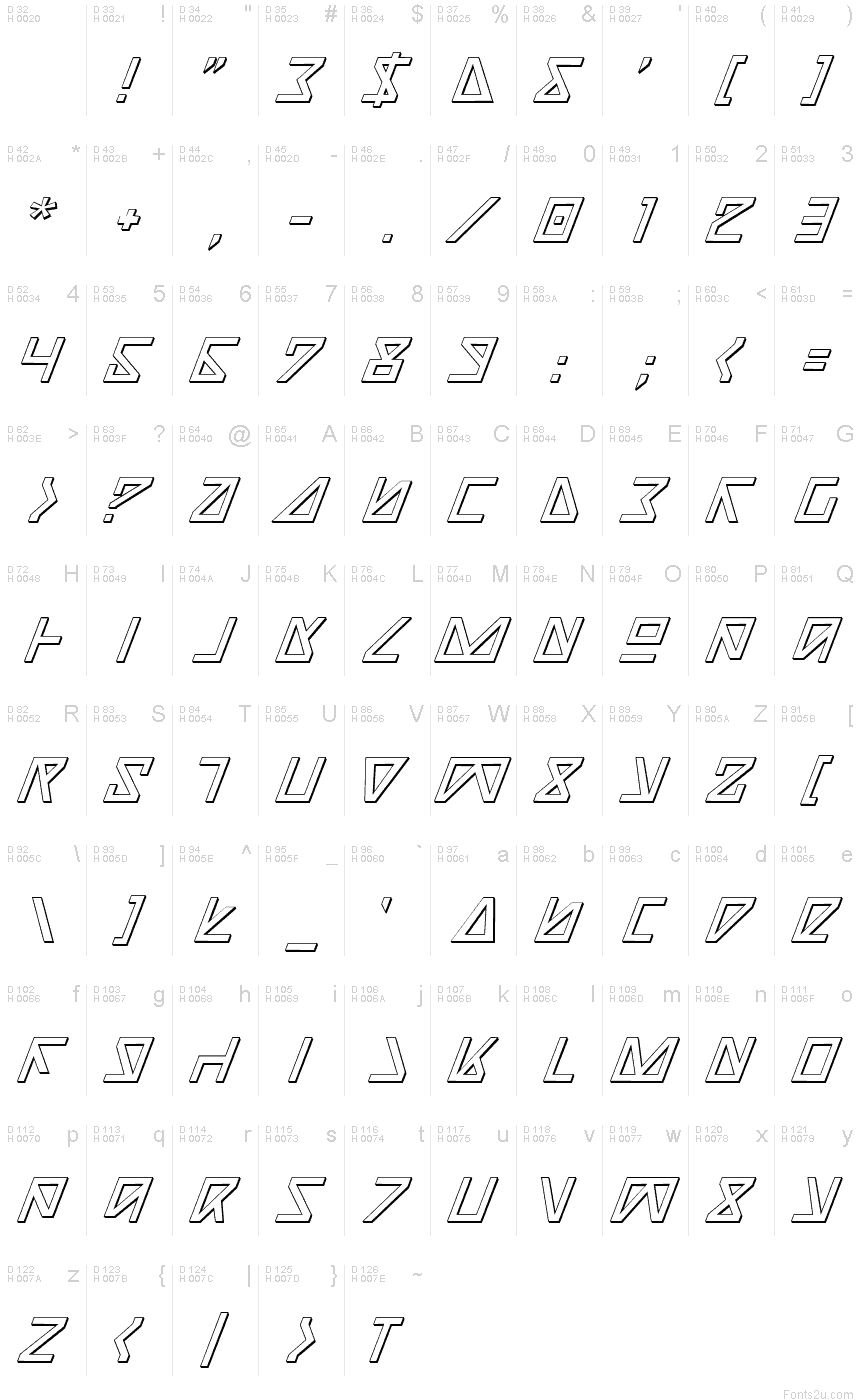
Nick Turbo Italic 3D to darmowy techniczny krój pisma typu display od Iconian Fonts. Wyróżnia się skośnymi, geometrycznymi konturami, ostrymi wcięciami i warstwowym efektem 3D, który nadaje każdemu znakowi wyścigowy, pochylony rytm. Kanciaste formy sprawiają, że projekt jest zwarty i mechaniczny, a otwarte wnętrza liter zapewniają czytelność nawet przy szybkim spojrzeniu.
Nick Turbo Italic 3D świetnie sprawdzi się w logotypach e-sportowych, tytułach gier, plakatach sci-fi, grafikach wyścigowych, okładkach albumów czy ulotkach eventowych. Jego pochylona dynamika i obrysowana konstrukcja wnoszą dużą dawkę wizualnej energii bez zbędnych zdobień. Ten darmowy font pasuje również do tekstów banerowych, ekranów startowych i nagłówków, gdzie potrzebujesz ostrego, technicznego wyglądu, który sprawia wrażenie zaprojektowanego, a nie ozdobnego.
Nick Turbo Italic 3D